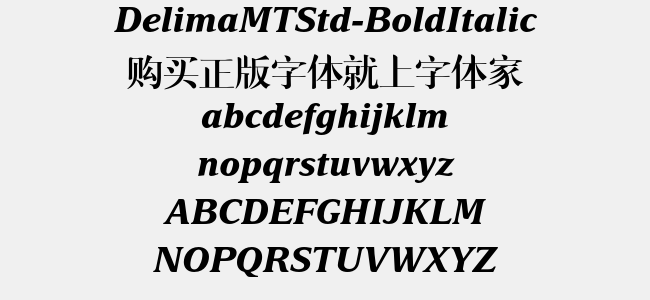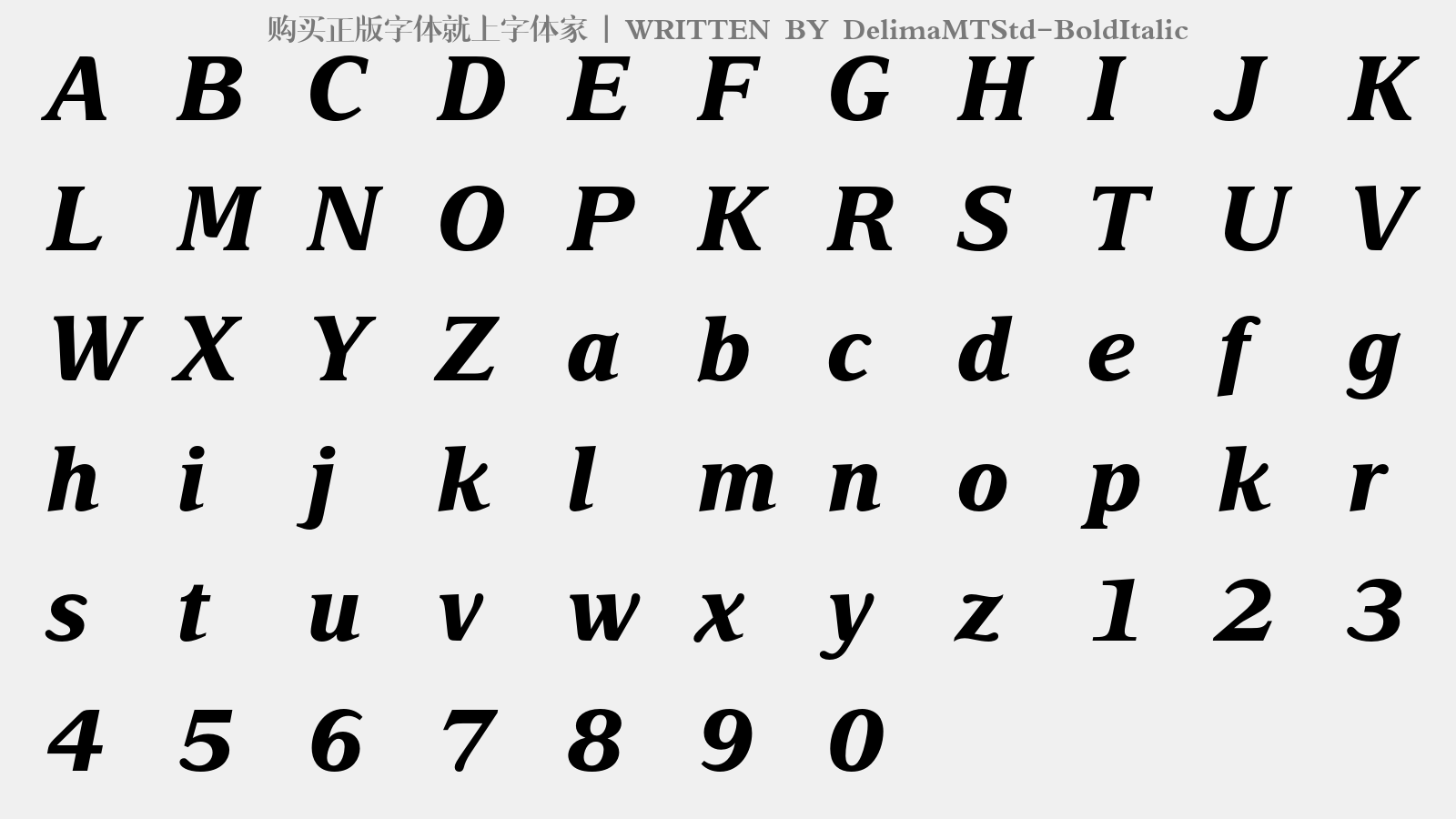
DelimaMTStd-BoldItalic
字体作者:现代字体
字体名称:DelimaMTStd-BoldItalic
字体字数:26个英文大小写字母及和阿拉伯数字
书体类型:英文类
该字体是一款个性独特的英文字体,非常适合创意类的PS字体,英文广告设计载体上使用,在设计中选择这款字体应用的话,会起到非常理想的效果。